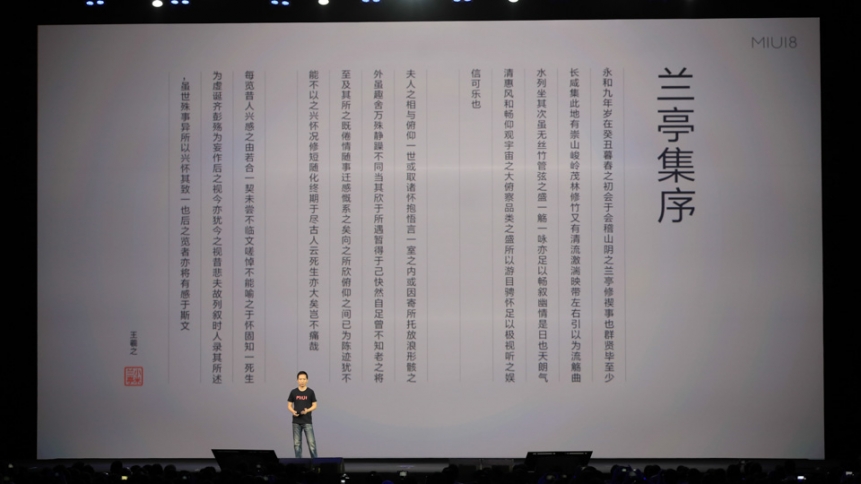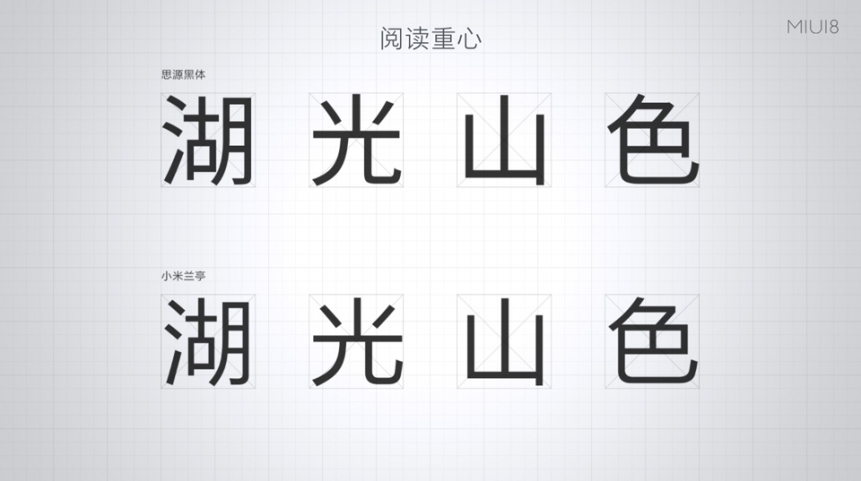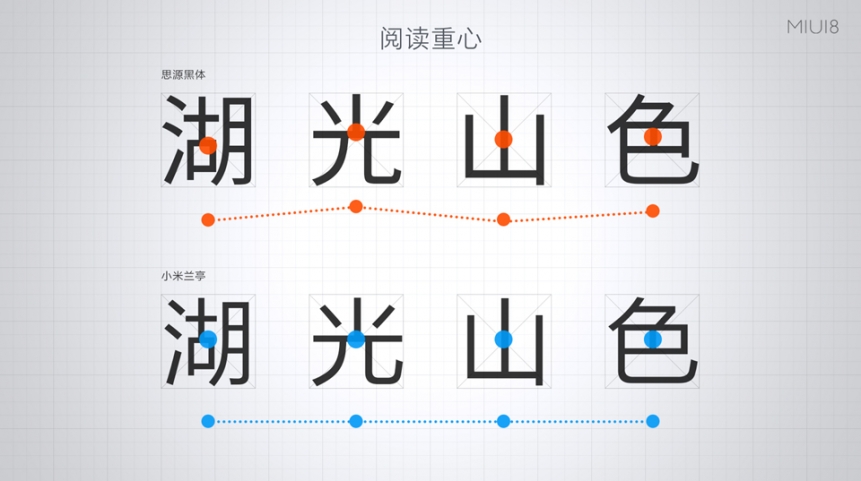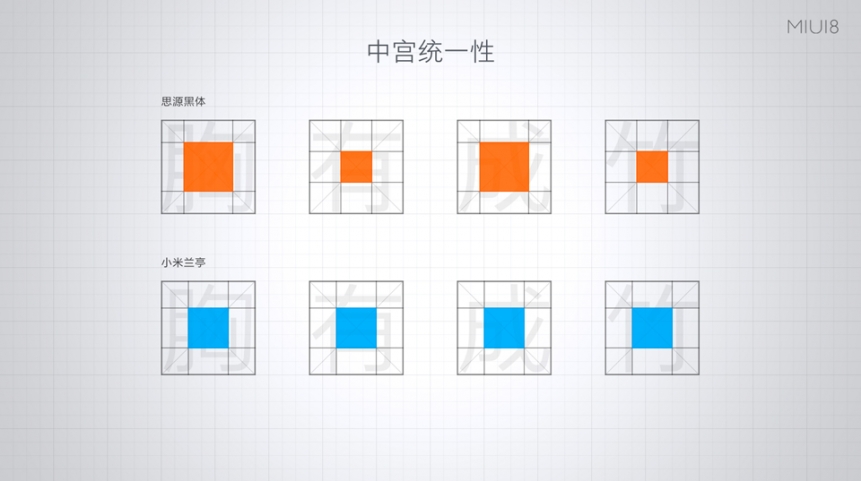
MIUI8小米兰亭字体
小米兰亭字体是小米MIUI8系统中的最新兰亭字体功能, miui系统中的小米兰亭字体看起来更加整齐,小米兰亭字体的特点是中宫,就是每个字的重心都在一条直线上,更加美观,便捷阅读~
而在MIUI 8中,小米还推出“小米兰亭”字体,经过18个月精心打磨,从中宫调整,到重心设计,全部根据移动互联网的展示和阅读特性做了细致的设计。
与方正合作,“小米兰亭”字体从6763个常用汉字、标点符号、拉丁字母,扩展到27533个汉字的全字库,号称要重新定义了小米手机的中文移动阅读体验。